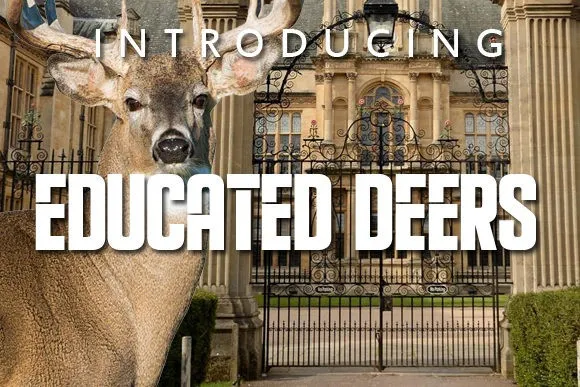
Educated Deers Font
Educated Deers é uma elegante fonte Sans Serif ideal para os profissionais que buscam criar design contemporâneo com toques vintage. Criação do designer Vladimir Nikolic, esta fonte combina um charme masculino moderno com um toque clássico e vintage. Perfeita tanto para logomarcas quanto para rótulos de produtos ou até mesmo posters, Educated Deers é uma opção versátil para designers que desejam dar um toque único e contemporâneo às suas criações. Sua simplicidade e sofisticação tornam-a a escolha perfeita quando se trata de adicionar um pouco mais de personalidade ao seu design, mantendo sempre o equilíbrio entre clássico e moderno. Não importa qual projeto estiver trabalhando, Educated Deers certamente será uma fonte que vai te ajudar a destacar no mercado de hoje.